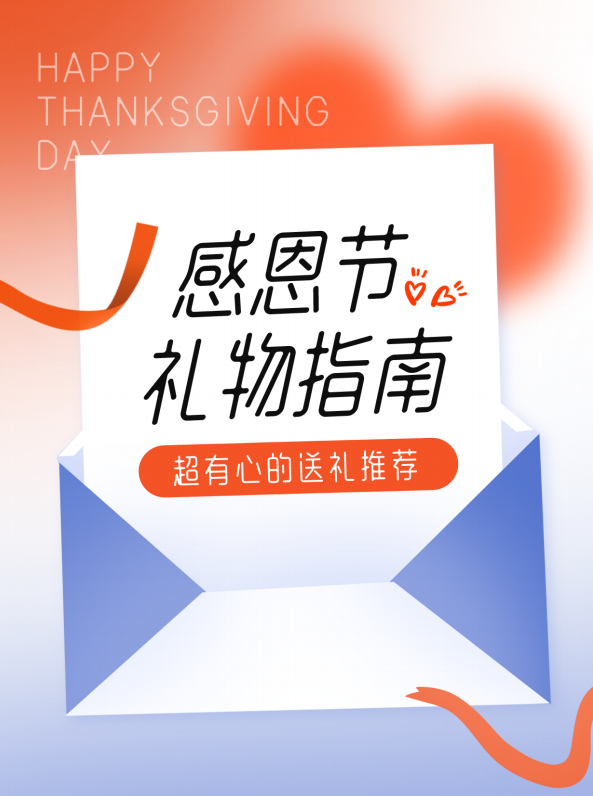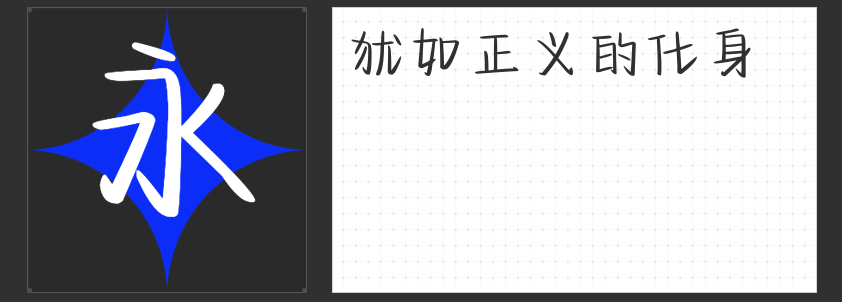
四款创意无限的短视频字体推荐
在短视频创作中,文字不仅是信息传递的载体,更是彰显个性与风格的重要元素。今天,就为大家推荐四款专为短视频定制的字体,它们各具特色,能够瞬间提升你的视频质感。
一、字恋狂漫野 絮风:手写感的直线艺术
这款字体以手写感为基础,结构张弛有度,布白空间通透,赋予了版面无限的活力。其笔画设计简洁而不失灵动,通过细微的大小变化和断开的处理,营造出一种错落有致的节奏感。无论是标题还是字幕,都能让你的短视频瞬间脱颖而出。
二、字恋狂澄空 絮风:灵活多变的手写新体验
与“漫野”相似,这款字体同样以手写感为核心,但字型上松下紧,重心略低,更显灵活多变。字间距的合理安排和丰富的单字结构变化,使得它在短视频中能够轻松吸引观众的眼球。简洁流畅的笔画与断开处理,让文字看起来更加轻盈、活泼。
三、高手庆科静雅体 古朴版:瘦长工整的圆体之选
如果你喜欢简洁而富有内涵的风格,那么这款字体绝对是你的不二之选。字型瘦长工整,布白均匀,重心平稳,给人一种宁静致远的感觉。整体圆角的处理和小连笔的设计,使得笔画软硬适中,更具美感。在短视频中,它能够为你的内容增添一份古朴与雅致。
四、字圈也字综艺弹幕体:张扬个性的综艺风
最后推荐的这款字体,专为综艺弹幕而生。横斜竖直、左低右高的字形结构,以及钝角与直角的巧妙结合,使得它充满了张扬与自信,仿佛在诉说着内心的故事。在短视频中,它能够瞬间点燃观众的热情,成为你内容的最佳点缀。
这四款字体各具特色,无论是手写感的细腻表达,还是综艺风的张扬个性,都能为你的短视频创作增添无限可能。快来试试吧!